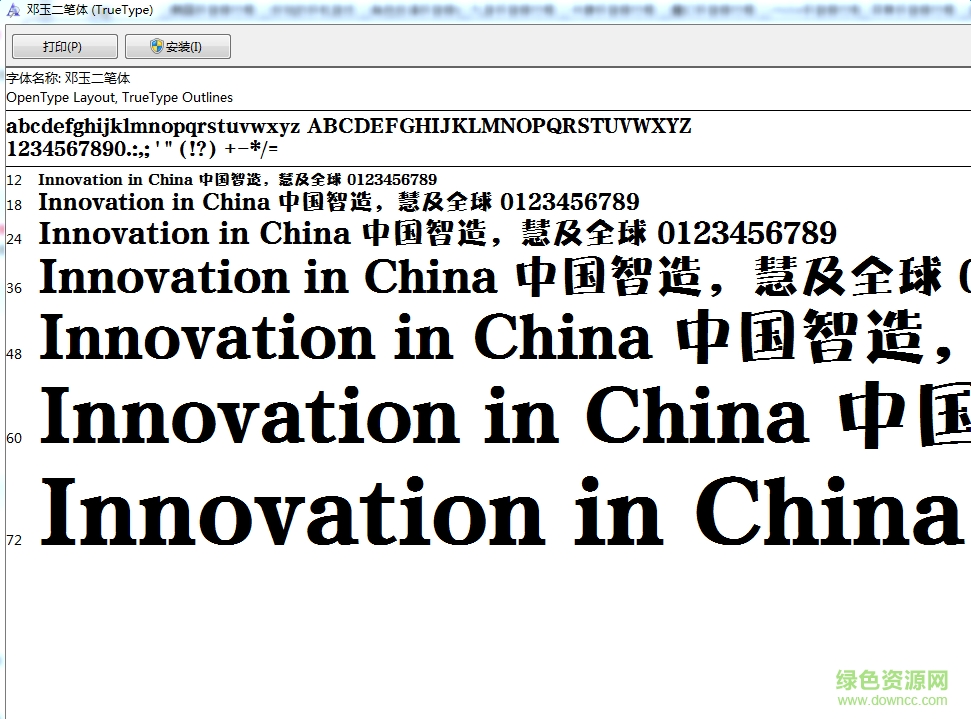
鄧玉二筆體是一款古典文雅風(fēng)格字體軟件,鄧玉二筆體細(xì)膩的橫筆畫配上粗獷的豎筆畫,非常有韻味,整體效果十分醒目,適用于各大海報廣告標(biāo)題的應(yīng)用,還有更多好看的字體歡迎來綠色資源網(wǎng)下載使用!
鄧玉二筆體是一款應(yīng)用于藝術(shù)設(shè)計方面的簡體中文字體,該字體筆畫粗壯,尾部的甩尾有力且有豐富的筆觸細(xì)節(jié),大字效果突出且引人注目;并且最大程度還原作者書寫字形,細(xì)節(jié)表現(xiàn)完整,且字庫完整,可以廣泛應(yīng)用于名片設(shè)計、新聞媒體、宣傳海報、ppt、影視制作以及內(nèi)容用字等領(lǐng)域。
此字體粗黑文雅,字跡一筆一畫工整務(wù)必,每個字體所占空間一致,整體效果非常正式,用來廣告設(shè)計印刷再合適不過了!